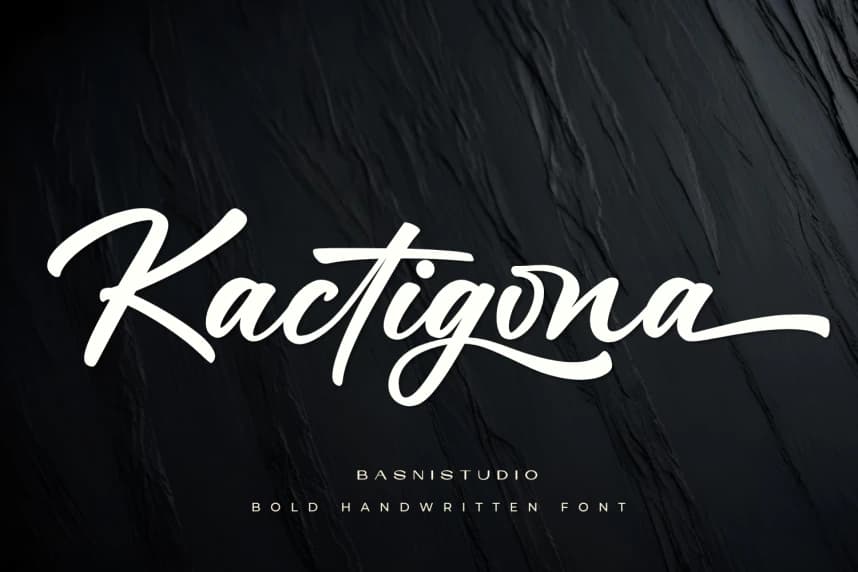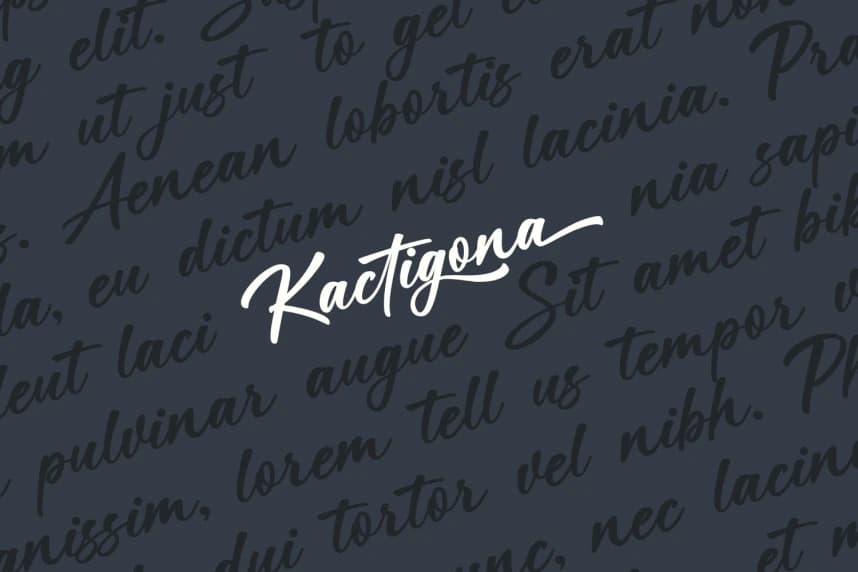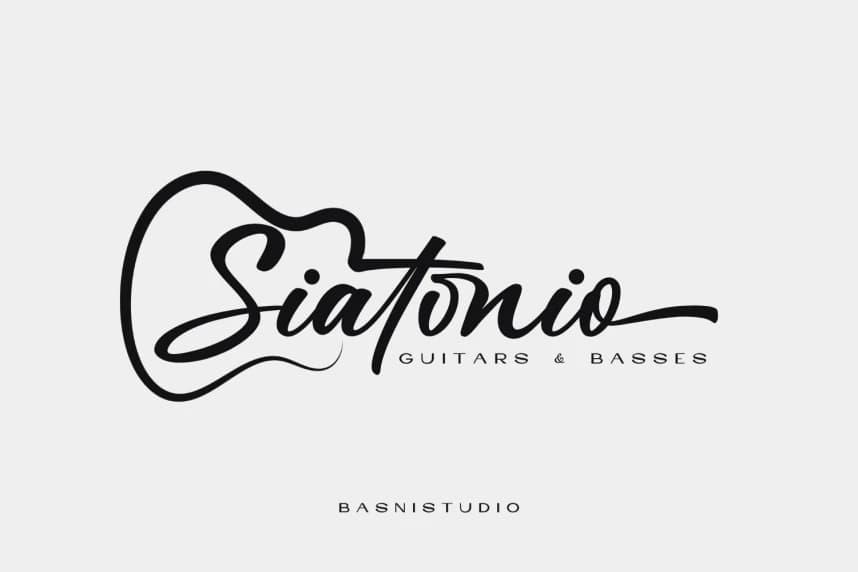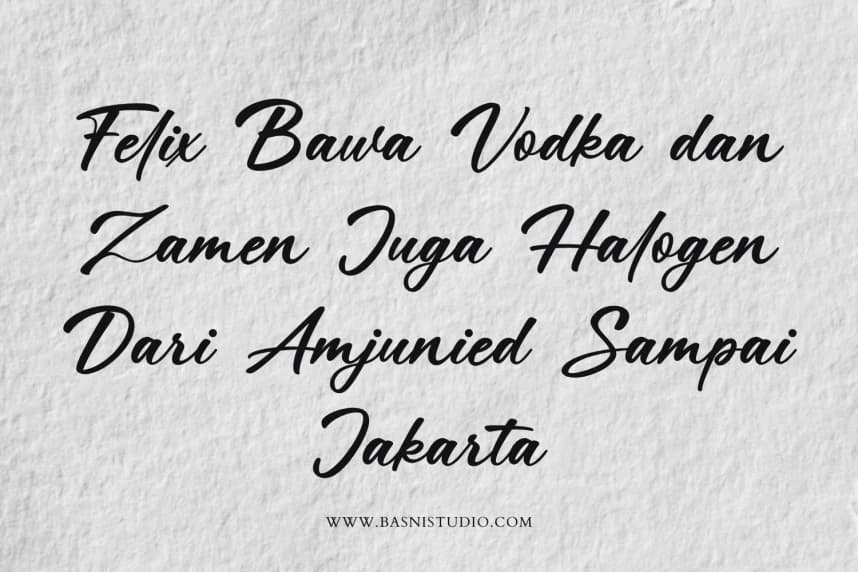
Kactigona – Bold Handwritten Font
Kactigona Bold el yazısı fontu, gerçek fırça ile üretilmiş özgün bir dokunuş sağlar; markalaşmadan sosyal medyaya, davetiyelerden ambalajlara kadar her şey için doğal ve cesur bir dokunuş.
Kactigona Bold el yazısı fontu, otantik fırça ile doğal ve cesur bir dokunuş için tasarlanmış; marka oluşturma ve sosyal medyadan davetiyelere ve ambalaja kadar her şey için.
Kactigona – Bold Handwritten